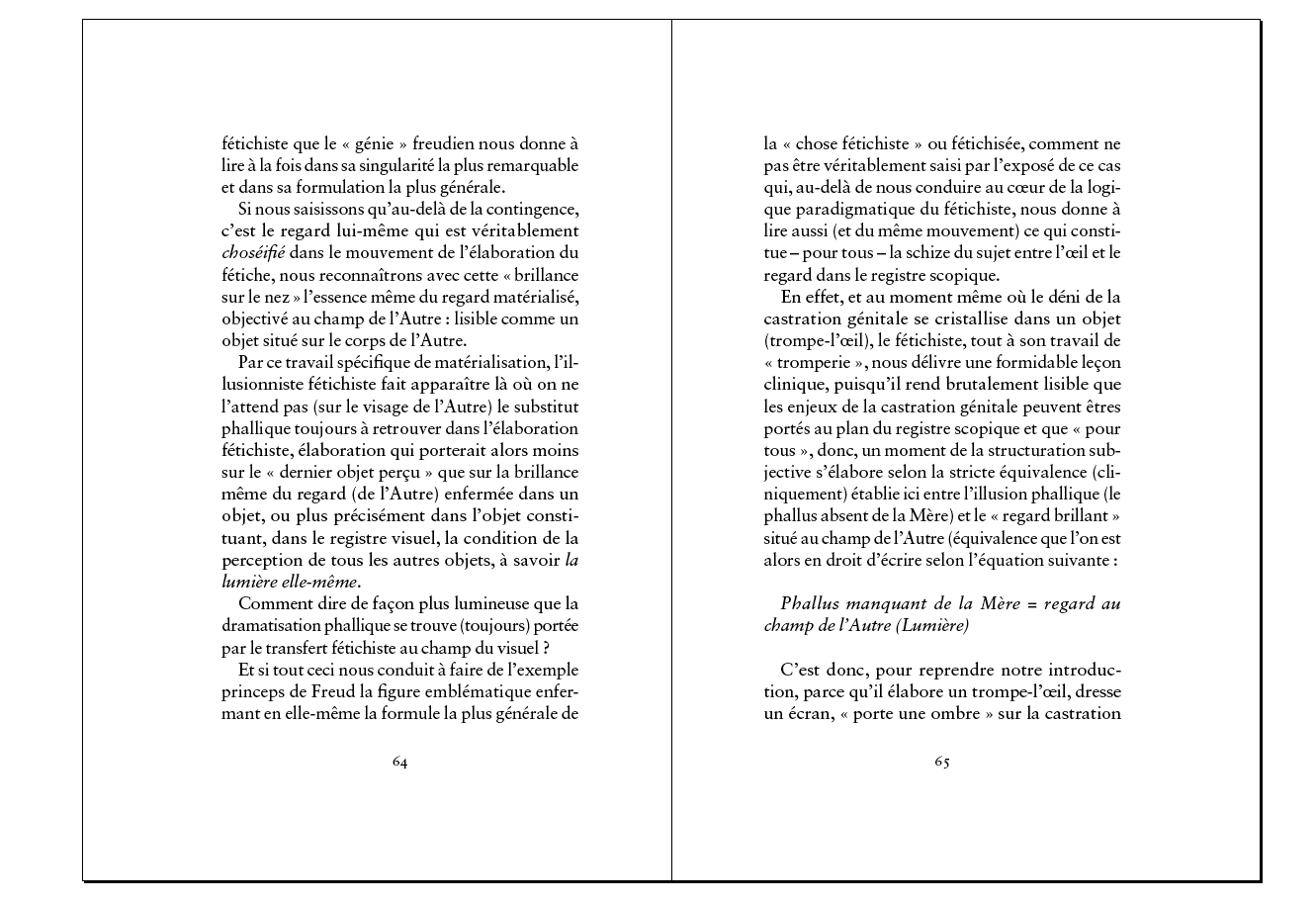
pas évident à juger sur 4 lignes de texte…
ci-joint mes essais de réglage pour l'intermots et l'interlettrage.
Concernant l'interlignage, il faudrait voir une page complète pour juger du gris.
À Frédéric Nolleau, j'ai lu cet article, mais le Sabon me pose néanmoins un problème particulier, (je ne suis pas sûr du terme) mais "l'oeil" des caractères semble très "ouvert/haut", à cela s'ajoute la présence d'un blanc important... Du coup, je n'arrive pas à régler l'interlignage de façon convenable... soit le texte est à l'étroit, soit il nage... (sur ID, je l'ai mis pour l'instant à 112 via le menu justification),